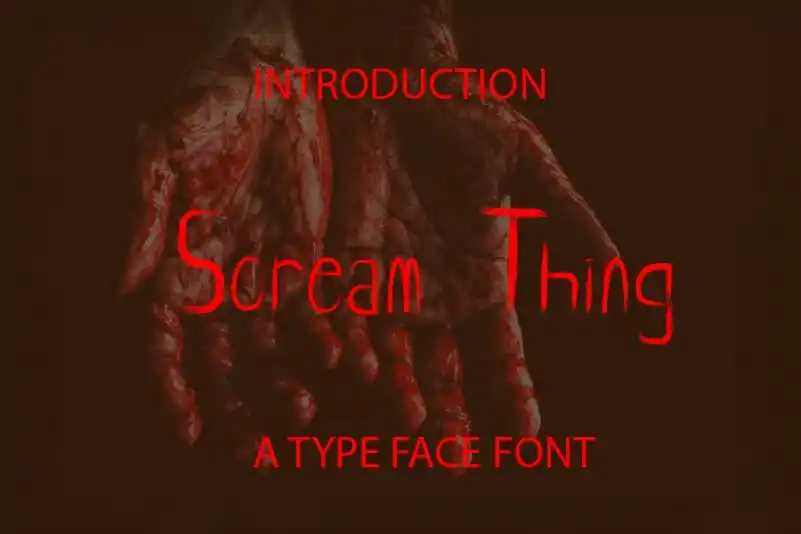
Scream Thing Script Font – Download Grátis
A Scream Thing Script Font surge inspirada no tipo de letra clássico encontrado nas legendas dos filmes de terror. Com sua escrita elaborada com uma intenção sobrenatural, esta fonte é perfeita para dar um toque especial às criações gráficas relacionadas ao gênero de horror. Seja ela o subtítulo da próxima sátira macabra ou a linha do logo de seu próximo estúdio cinematográfico de terror, a Scream Thing Script Font certamente dará aquele brilho extra que você precisa para fazer um design realmente notável e impactante. É uma escolha perfeita para quem procura aquela pitada sobrenatural para seus projetos gráficos. Edy Isti Studio criou esta fonte com todo o cuidado, tornando-a não apenas uma opção elegante de script, mas também um elemento poderoso que pode elevar qualquer projeto de horror ao próximo nível.